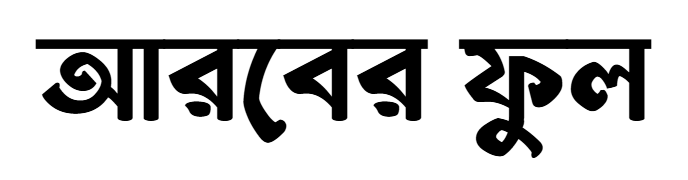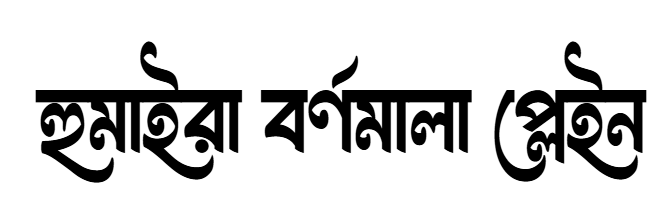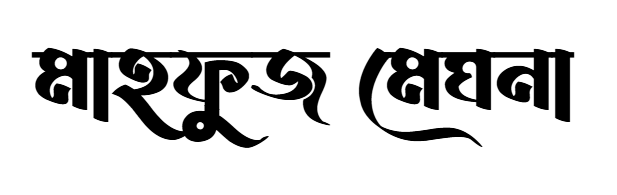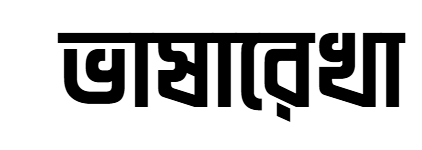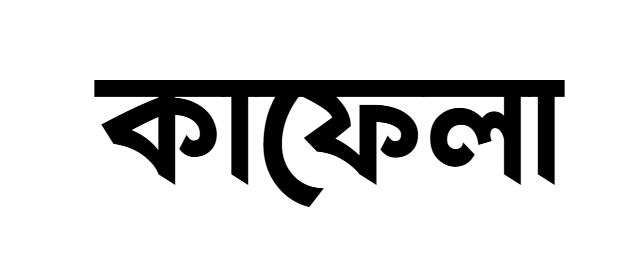
Stylish Bangla Fonts for Social Media Content
বাংলাদেশের content creators, graphic designers, Instagram posters, TikTok storytellers, এবং Facebook marketers যারা eye catching Bangla typography চান, এই articleটা ঠিক আপনার জন্য. Social media এ audience ধরে রাখা আর engagement বাড়ানোর জন্য font choice অনেক বড় factor. আজ আমরা কিছু best Stylish Bangla fonts for social media content review করবো, যাতে আপনি সহজেই বুঝতে পারেন কোনটা কই use করবেন.
1. Kafela Stylish Font
Kafela দেখতে modern, পরিষ্কার এবং screen-friendly. Bangla letters-এর shapeটা balanced, তাই social design-এ headline কিংবা bold caption-এ use করলে ভালো লাগে.
প্রায়োগিক ব্যবহার
• Instagram & Facebook headline
• Poster title
• Reels cover caption
কেন ভালো
• Clean look থাকায় long text-এও readability টিকে থাকে
• Professional design feel
Cons:
style options খুব বেশি নেই, তাই যদি dramatic look চান তাহলে একটু limit অনুভব হতে পারে।
Social media impact
যদি আপনার post creative এবং professional ধরে রাখতে চান, Kafela headline ও carousel title-এ বরাবরই safe choice।
2. Bhasha Rekha Font
Classic এবং subtle, traditional Bangla-এর সঙ্গে modern touch মিশে। small sizes-এও pixel-wise clean পড়ে।
প্রায়োগিক ব্যবহার
• Story text
• Captions
• Overlay text graphics
কেন ভালো
legibility ভালো, প্রতিটি চরিত্র ঠিকঠাক স্পষ্ট।
Cons:
bold dramatic effect কম।
Social media impact
Quote posts বা CTA (call to action) text-এ ব্যবহার করলে audience সহজে পড়ে নেয়।
3. Humaira Bornomala (Plain Version)
Humaira Bornomala একটা soft, human-touch Bangla font। দেখলে মনে হয় handwritten vibe আছে, কিন্তু অতটা decorative না যে পড়তে সমস্যা হবে। Social media-তে যেখানে emotion, feeling বা storytelling দরকার, সেখানে এই font naturally কাজ করে।
কেন Social Media-তে ভালো কাজ করে
এই font-এর letter spacing আর stroke weight এমনভাবে ডিজাইন করা যে mobile screen-এও চোখে চাপ পড়ে না। Instagram story, Facebook quote post, বা motivational text-এ মানুষ সাধারণত পুরো লেখাটা পড়ে, skip করে না।
Best Use Case
• Quote graphics (motivational, romantic, life advice)
• Instagram story text
• Facebook post image captions
• Brand storytelling content
কোথায় ব্যবহার না করাই ভালো
• Bold headline
• Offer banner
• CTA button text
Pro Tip
Light background + dark text দিলে Humaira Bornomala সবচেয়ে ভালো দেখায়। Background বেশি busy হলে font-এর softness হারিয়ে যায়।
4. Badhon 17
Badhon 17 হচ্ছে playful এবং casual Bangla font। এটা formal বা corporate না। Youth content, entertainment page, meme-style post-এর জন্য বানানো font বললেই ঠিক হবে।
কেন Social Media-তে ভালো কাজ করে
Bangladeshi audience casual content খুব দ্রুত relate করে। Badhon 17 সেই relatable vibe দেয়। Font-টা দেখলেই মনে হয় friendly, rigid না।
Best Use Case
• Meme text
• Fun captions
• Youth-oriented Facebook pages
• Entertainment reels cover
কোথায় ব্যবহার না করাই ভালো
• Business announcement
• Serious educational content
• Brand guideline strict হলে
Pro Tip
Emoji বা icon-এর সাথে mix করলে এই font বেশি জীবন্ত লাগে। Pure text design-এ না, একটু fun element রাখো।
5. Arober Ful
Arober Ful একটা decorative Bangla font। নাম থেকেই বোঝা যায়, ফুল-এর মতো aesthetic। এটা everyday font না, এটা special occasion-এর জন্য।
কেন Social Media-তে আলাদা দেখায়
সবাই clean font ব্যবহার করে। Arober Ful ব্যবহার করলে post instantly আলাদা লাগে। Especially festive content-এ এই font visual attention বাড়ায়।
Best Use Case
• Eid, Puja, special day posts
• Invitation graphics
• Event poster title
• Decorative heading
কোথায় ব্যবহার না করাই ভালো
• Long paragraph
• Caption text
• CTA button
Pro Tip
একটা design-এ max 5–6 শব্দের বেশি Arober Ful ব্যবহার করো না। বেশি text দিলে readability নষ্ট হয়।
6. Mahfuj Megna Font
Mahfuj Megna smooth এবং calm font। খুব বেশি bold না, আবার খুব thin-ও না। Natural flow আছে, চোখে শান্ত লাগে।
কেন Social Media-তে ভালো কাজ করে
Lifestyle, personal branding, educational content-এ মানুষ aggressive design পছন্দ করে না। Megna font সেখানে balance আনে।
Best Use Case
• Educational slides
• Carousel post text
• Personal brand content
• Explainer graphics
কোথায় ব্যবহার না করাই ভালো
• High-impact sales banner
• Flashy offer post
Pro Tip
Megna font-টা gradient background বা soft color palette-এর সাথে খুব ভালো যায়। Hard contrast এ একটু flat লাগে।
একটা common mistake অনেকেই করে
একটা font সব জায়গায় ব্যবহার করা।
Smart approach হবে
• Headline এর জন্য এক font
• Body বা quote text-এর জন্য আলাদা font
• Decorative font শুধু special occasion-এ
এইভাবেই Stylish Bangla fonts for social media content সত্যিকারে কাজ করবে, শুধু সুন্দর না, effective হবে।